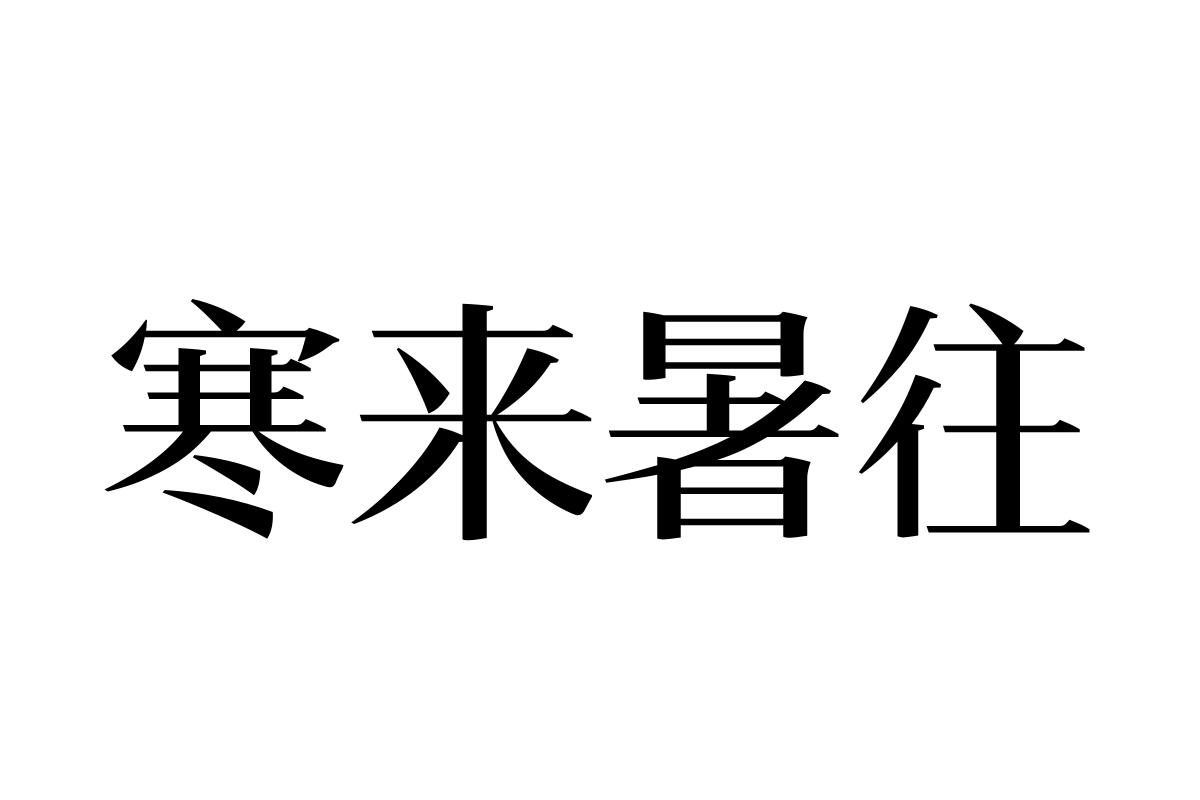
汉仪瑞意宋 50_Text_W是一款适用于中文排版的字体,主要用于书籍、报纸、杂志、广告等印刷品。这款字体的特点是字形端正,笔画流畅,适合用于正式场合的文本排版。同时,这款字体也具有较高的识别度和辨识性,能够有效地提升文本的可读性和美观度。
汉仪瑞意宋 50_Text_W的笔画粗细适中,既有楷书的规整,又有行书的灵动,使得整个字体既有传统的韵味,又不失现代感。此外,这款字体还具有一定的装饰性,如在部分字中加入了一些装饰性的笔画或图案,使得整个字体更加生动有趣。
总的来说,汉仪瑞意宋 50_Text_W是一款非常实用的字体,无论是在商业还是教育领域,都有很好的应用前景。